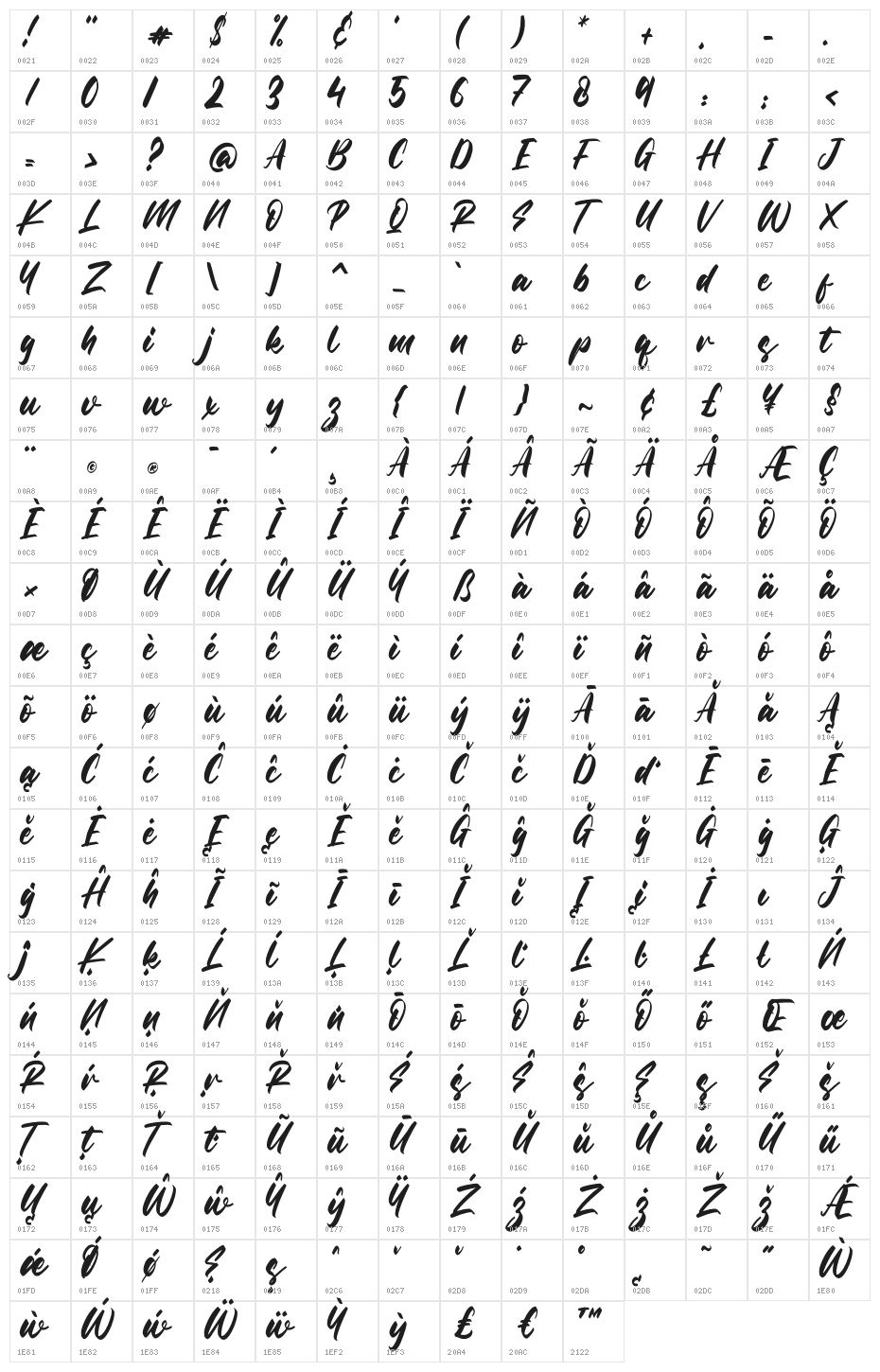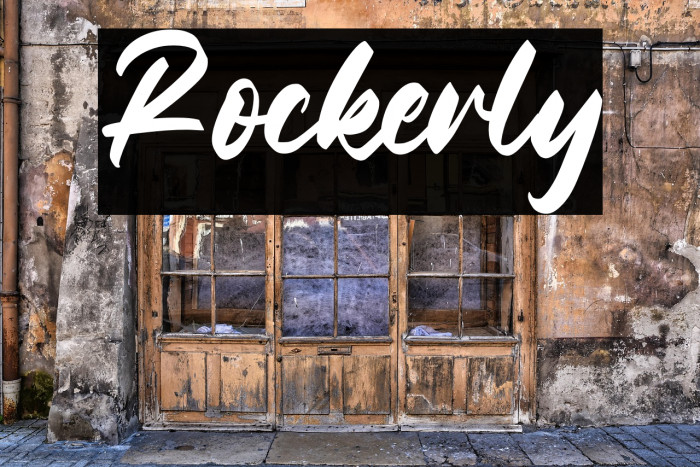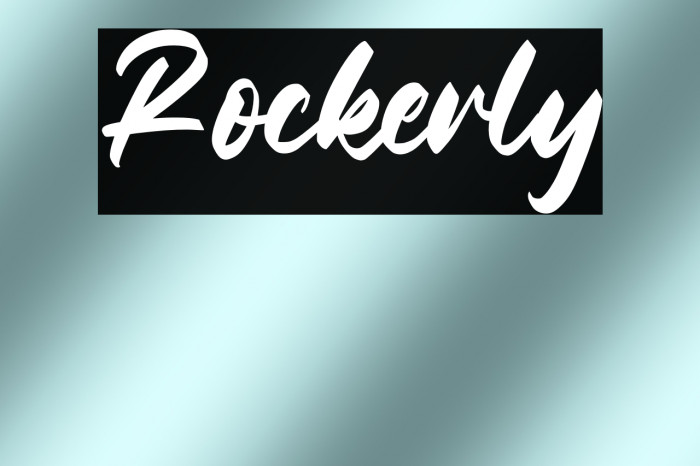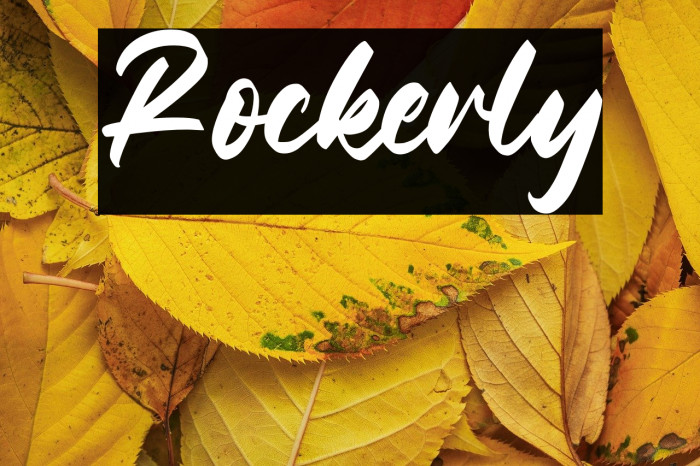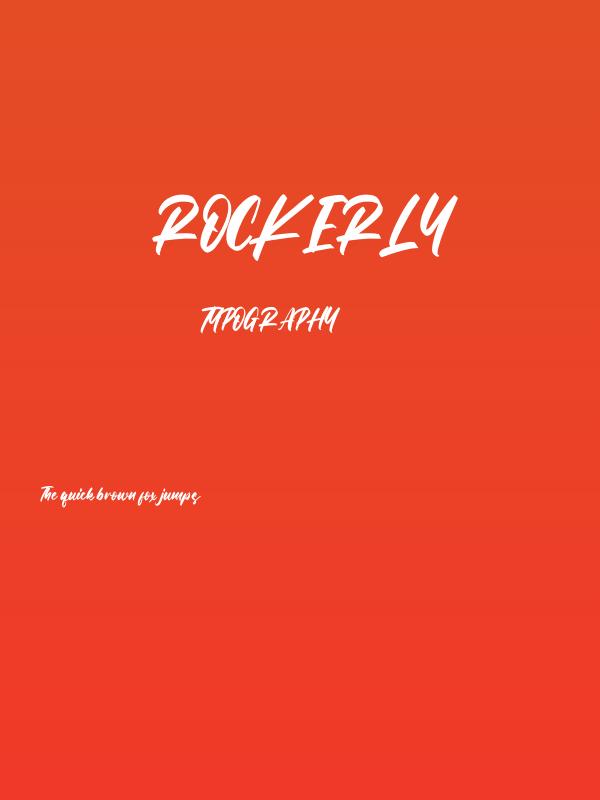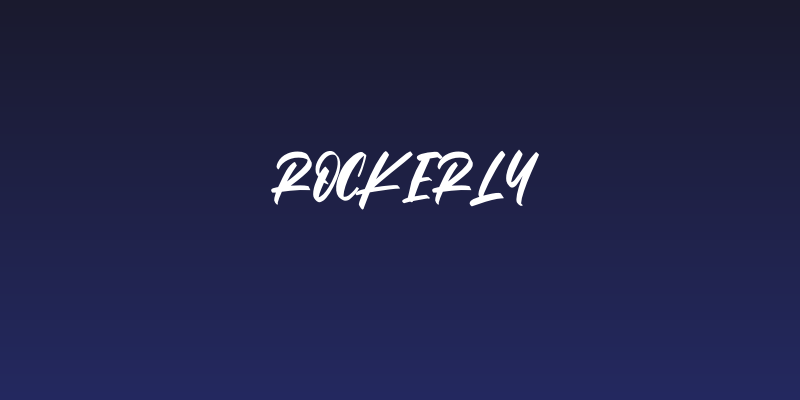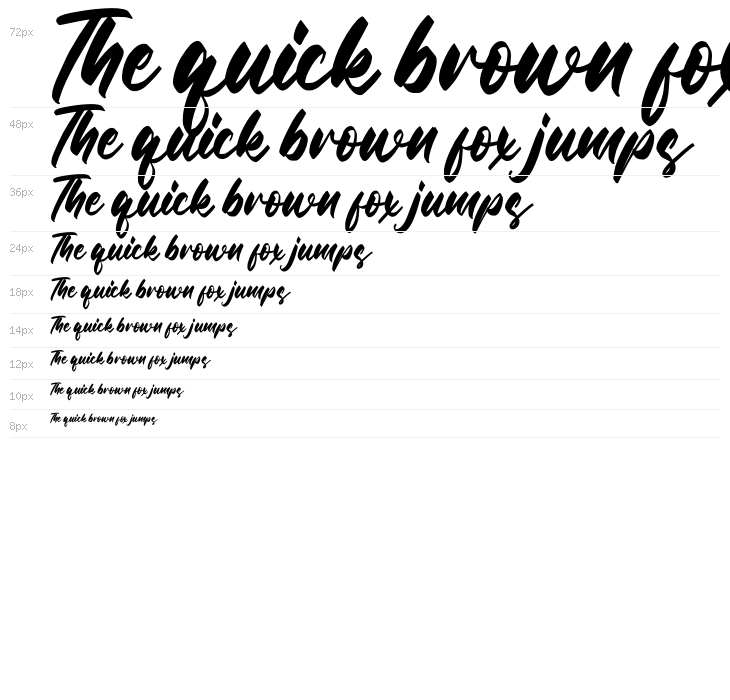
Rockerly Font
| Nome | Rockerly |
| Progetti proposti | Ideal for projects needing a vibrant and energetic touch, such as posters, branding, and social media graphics. |